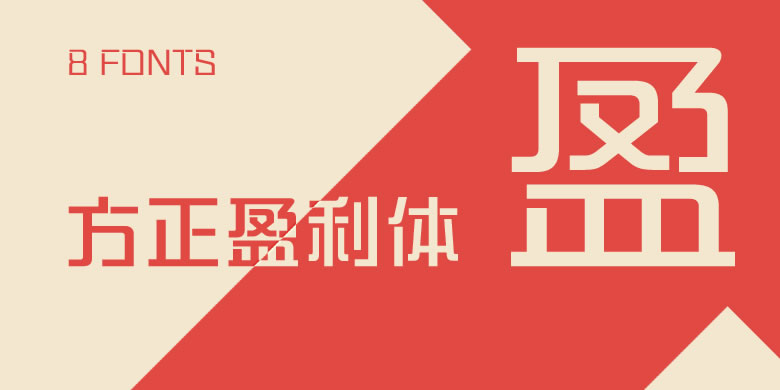
品牌:方正字库设计师:郭炳权发行时间:2017字库编码:大陆简体(GB2312-80)、简繁扩展(GBK)分类:创意字体
方正盈利体系列
方正盈利体是一款几何感十足的创意字体。其笔画多以对称的手法来表现,撇、捺都有明显的几何转折,不同于书写状态的连续弧线。右上的折笔处改为圆角,使字体刚中带柔。在笔画中加入喷漆字的断笔效果,形成一种特有的视觉个性。方正盈利体家族包含8款字重,个性简洁明快,亲和力强,适用于书刊封面、品牌广告和产品包装设计。